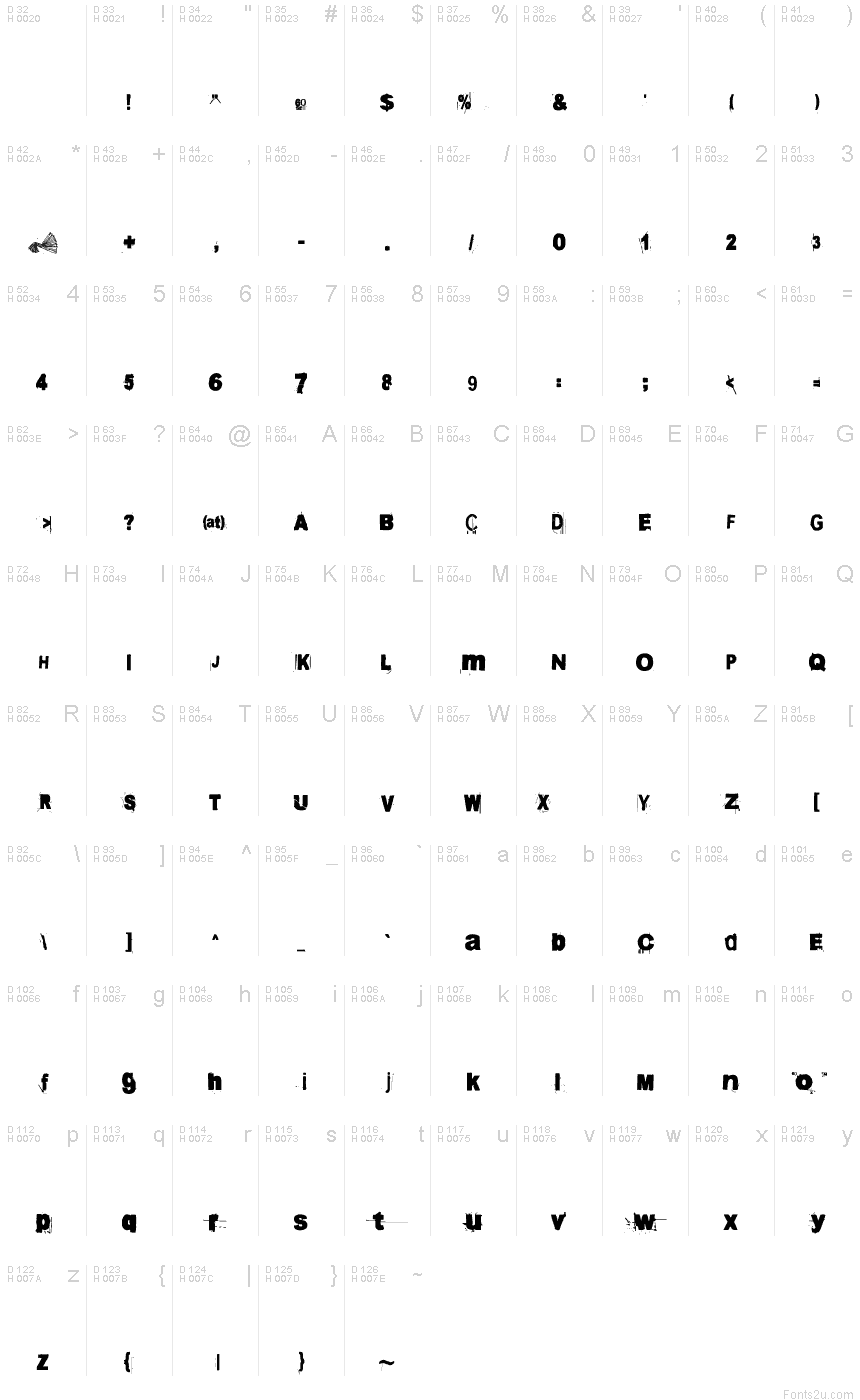
60sekuntia
60 Sekuntia to darmowy, distressed krój typu display o surowym, kolażowym charakterze, przypominającym estetykę punkowych ulotek i fanzinów. Litery są ciężkie i masywne, a ich krawędzie wyglądają na poszarpane, nadgryzione i nieco niestabilne. Dzięki nagłym załamaniom i nierównym łączeniom, całość sprawia wrażenie pilności, a nie uporządkowanego projektu.
Świetnie sprawdzi się na plakatach, okładkach płyt, grafikach streetwearowych, planszach tytułowych, w identyfikacji wydarzeń czy krótkich nagłówkach, gdzie przekaz potrzebuje surowego, ręcznego akcentu. Jako darmowy font, sprawdzi się również w monogramach, inicjałach czy krótkich logotypach – masywne kształty trzymają formę, a sfatygowana sylwetka robi całą robotę.